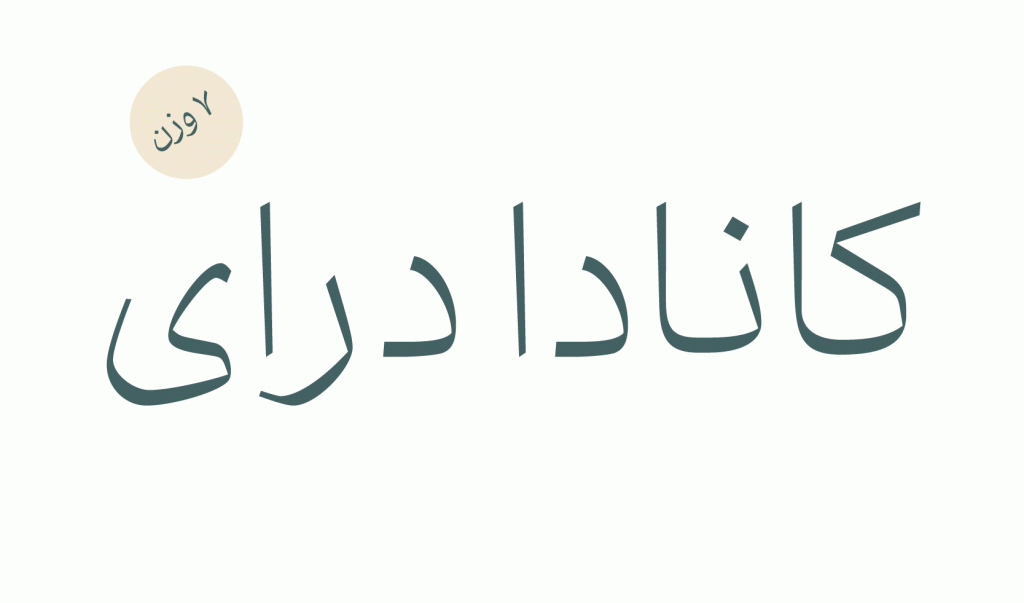
گلیف فرانکلین
فونت فرانکلین ترکیبی از خانواده نسخ به همراه شاکله فرم های هندسی می باشد. این تایپ فیس با قیمتی مقرون به صرفه تر از سایرین دارای 7 وزن مجزا برای شما دوستان عزیز ارائه گردیده است.
نسخ
فونت فرانکلین
فونت فرانکلین تایپ فیسی که تلاشی دقیق و مداوم در ایجاد و توسعه آن با توجه به ظرافت های خاص آن به سبب افزایش خوانایی بیشتر و همچنین جاذبه های بصری آن گردیده است. همت مضاعفی که در انسجام کلمات به کمک تنظیم دقیق فاصله‌ی حروف بوده انجام شده است.
همانطور که گفته شد خوانایی بالای این قلم به سبب رعایت جزئیات وظرافت های طراحی امری مهم و از اولویت های طراحی این تایپ فیس بوده است. با دقت در فرانکلین می توان دریافت که به نوعی این قلم الهام و اقتباس گرفته شده از خط خوشنویسی نسخ و خانواده هندسی می باشد. رعایت قوائد موجود در نسخ و گاها طراحی و اقتباس قسمت هایی از آن بر اساس مدل هندسی از ویژگی های اصلی این فرانکلین می باشد.
فرانکلین و تلاشی در خلق سبکی جدید
با اندکی دقت در فرانکلین می توان دریافت که شخصیتی جدی و جسور دارد. مناسب برای متون مطبوعاتی و فضای وب دارد همچنین در ارائه تیتر ها و عناوین تبلیغاتی برای جذب نگاه مخاطبین حرف ها برای گفتن دارد . زوایای داخلی و خارجی تند و تیز و در فرم های و درو های طراحی فرانکلین بسیار است حال آنکه از سطوح نرم و فرم های هموار نیز بهره می برد.
از دیگر ویژگی های فونت فرانکلین می توان به پشتیبانی از چندین زبان مختلف و اعراب و نشانه ها نیز اشاره کرد. از جمله این زبان ها می توان به عربی و … اشاره نمود.
زبان‌های پشتیبانی شده :
فارسی ، عربی
7 وزن
پشتیبانی اعداد فارسی:
این قلم از زبان فارسی و عربی پشتیبانی می‌کند.